蘋果在 Apple Watch 出貨的時候,正式公開了 San Francisco 這個清晰易明的字型,但是蘋果對於字型可易程度的野心不止於此,據美國網站流出的一些蘋果準備文件得知,蘋果欲在下一代 iOS 和 Mac 採用 Apple Watch 的字型,改善易讀程度。
據蘋果內部一些準備文件透露,蘋果欲在未來推出的 iOS 9 和 OSX 10.11「Gala」採用 Apple Watch 現時使用的字型 San Francisco,取代從 iOS 7 和 OSX Yosemite 開始使用但一直被批評可讀性極低的 Helvetica Neue。過去率先採用 San Francisco 這個字型的是 Apple Watch,因為要遷就手錶螢幕的大小,所以蘋果特別設計這個字型,令線條更明顯、可閱讀程度更好,而且可以動態縮放,字體大小不會影響可讀程度,而且熟悉這段消息的人士表示蘋果高層希望以全新外觀為 iOS 和 OSX 帶來全新體驗。唯獨部分使用蘋果工程師批評在非 Retina 螢幕使用這字型會不太好看。
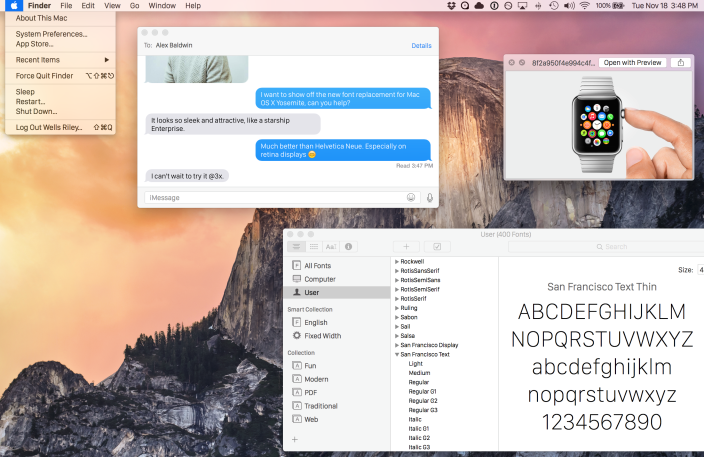
傳統上,在 6 月舉行的 WWDC 是發佈新 iOS 甚至 Mac 機 beta 版的大日子,到時我們就知道蘋果是否在新一代 iOS 和 OSX 採用 Apple Watch 的字型。同時,如果英文字型更改,中文字型會否同時更改?